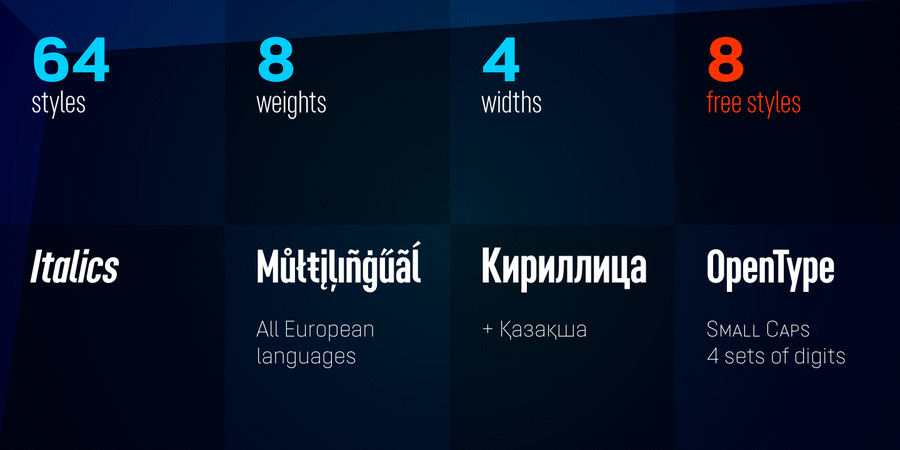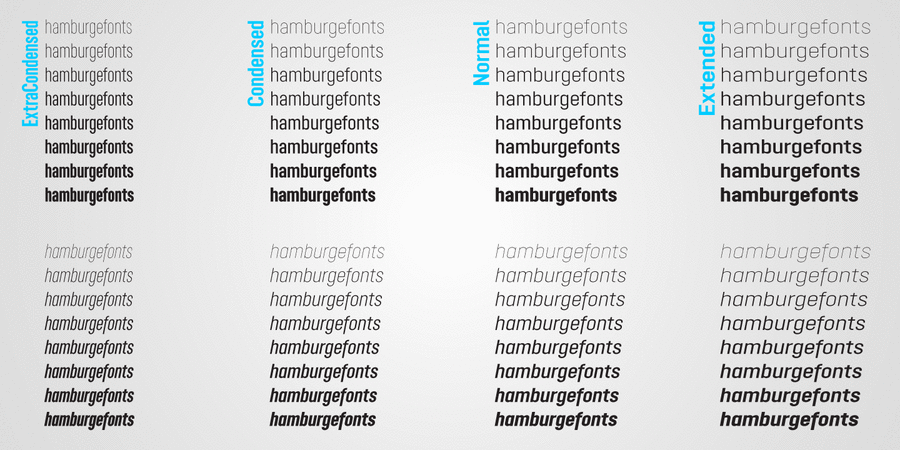
Опис гарнітури Opinion Pro — геометричний гротеск, що складається з 64 накреслень. Він містить 4 градації ширини (ExtraCondensed, Normal та Extended), кожна з яких складається з 8 насиченостей та відповідних курсивів. Жорсткі криві та виражені вертикальні штрихи роблять Opinion Pro доцільним як для акциденціі, так і для набору, зокрема для технічних цілей та навігації.
Opinion Pro підтримує велику кількість мов, серед яких усі європейські мови, засновані на латинці, основні кириличні мови, а також казахську кирилицю. Підтримка OpenType включає, окрім іншого, 4 набори цифр, капітель, верхні літерні індекси.
Шрифт розробив Олег Ліщук у студії Mint Type у 2017 році.